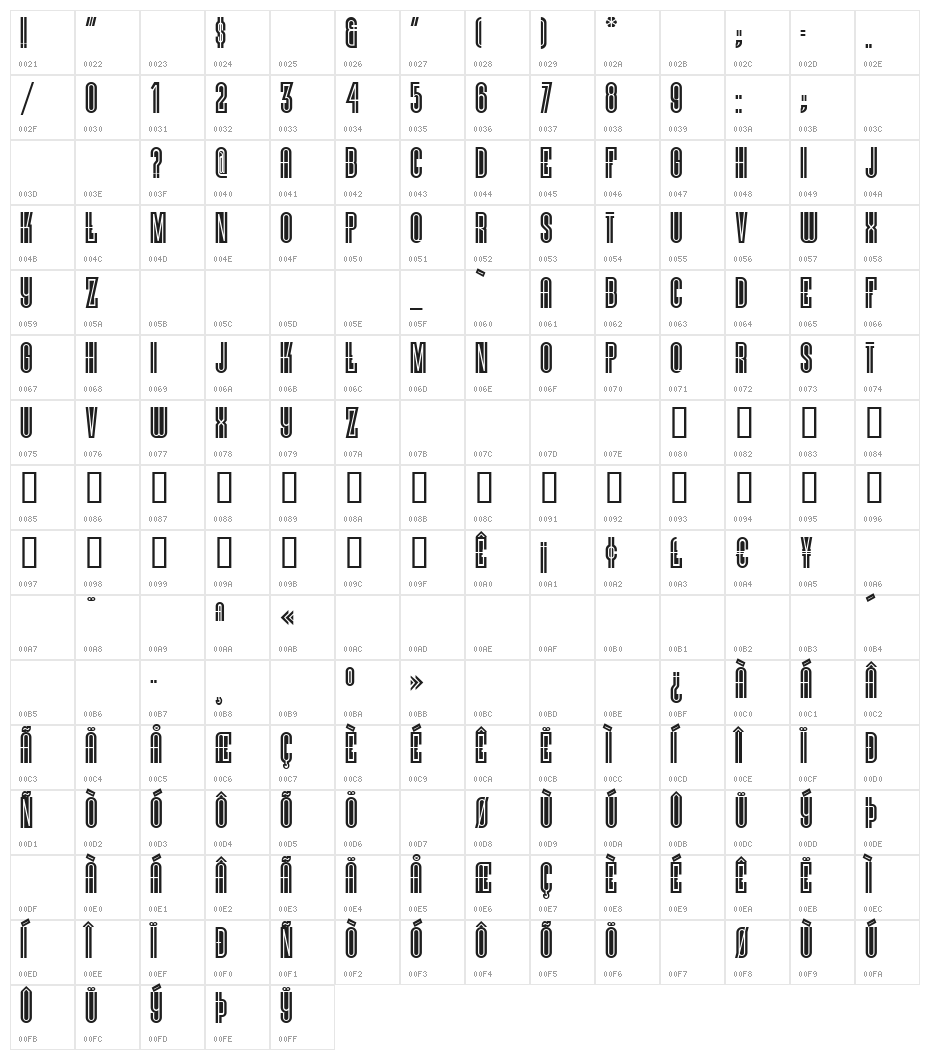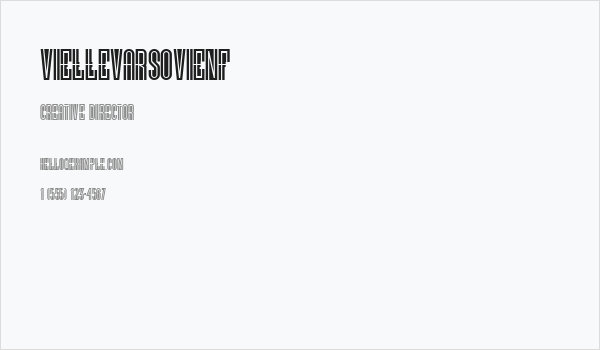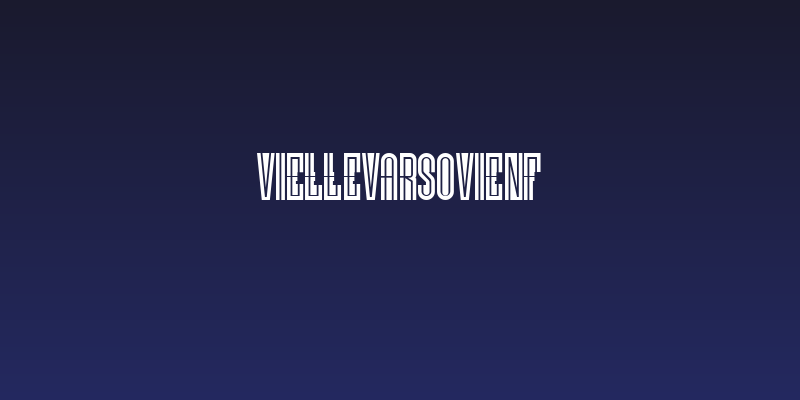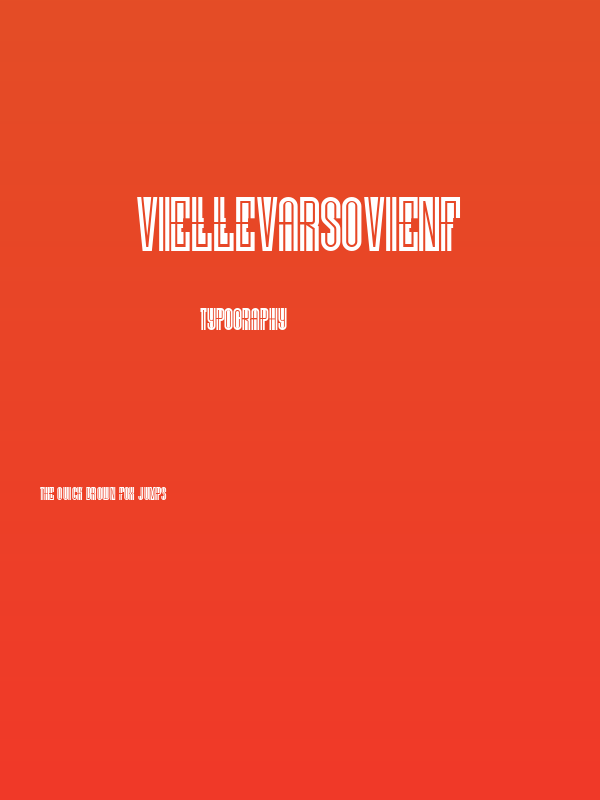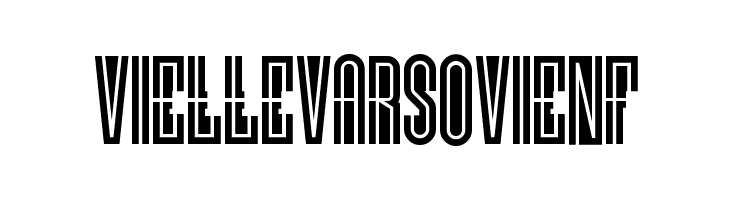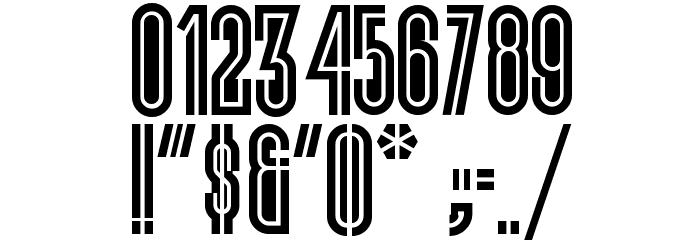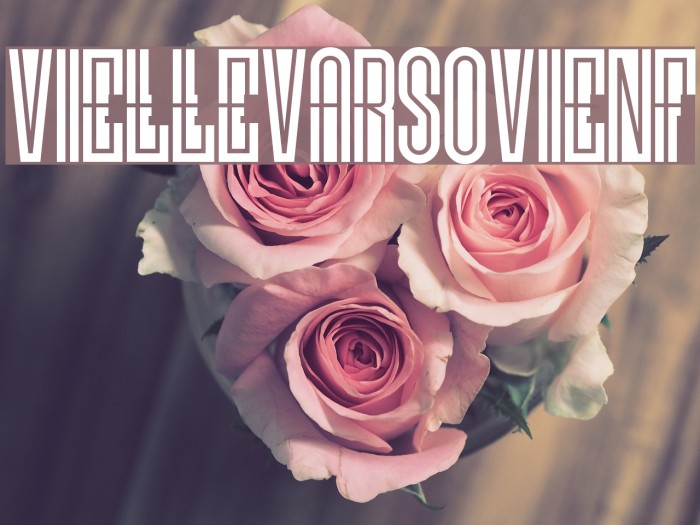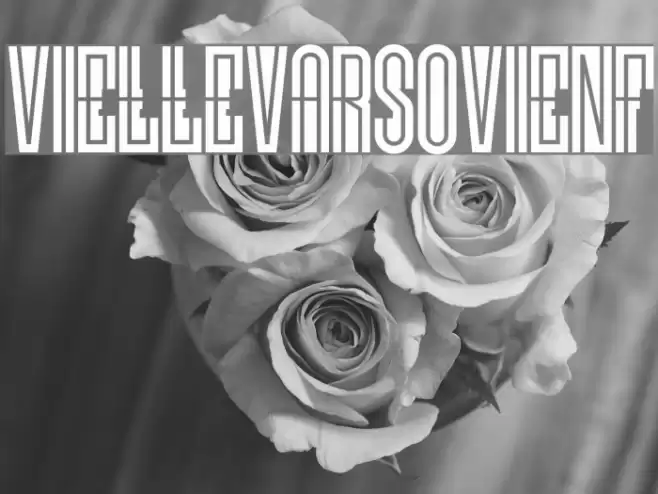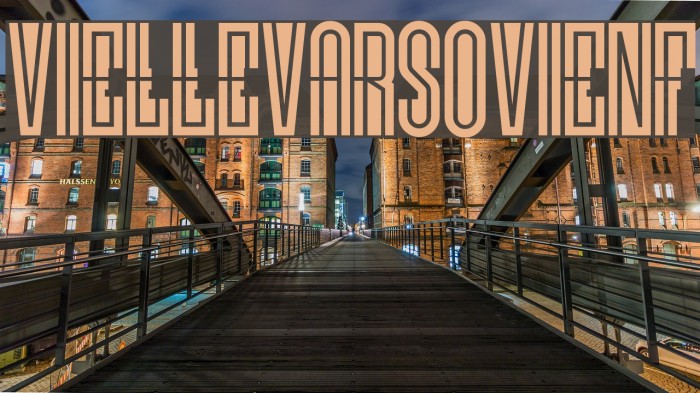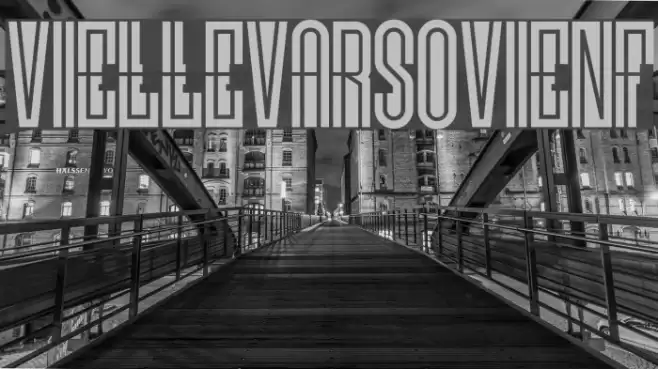
VielleVarsovieNF Font
✎ Futuristic
| Vorgeschlagene Projekte | Ideal for posters, branding, and editorial design where a strong, modern impact is desired. |